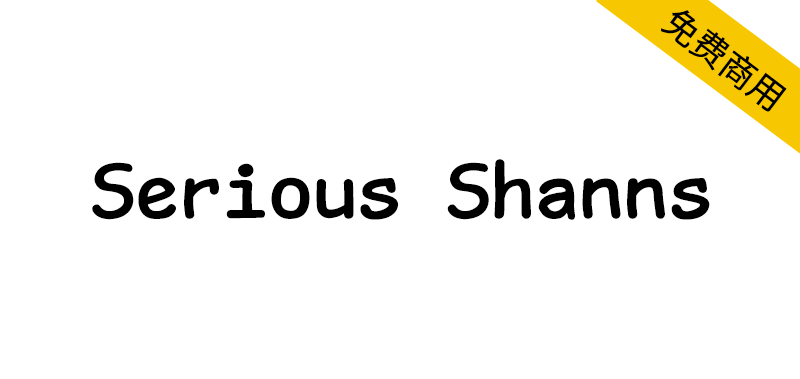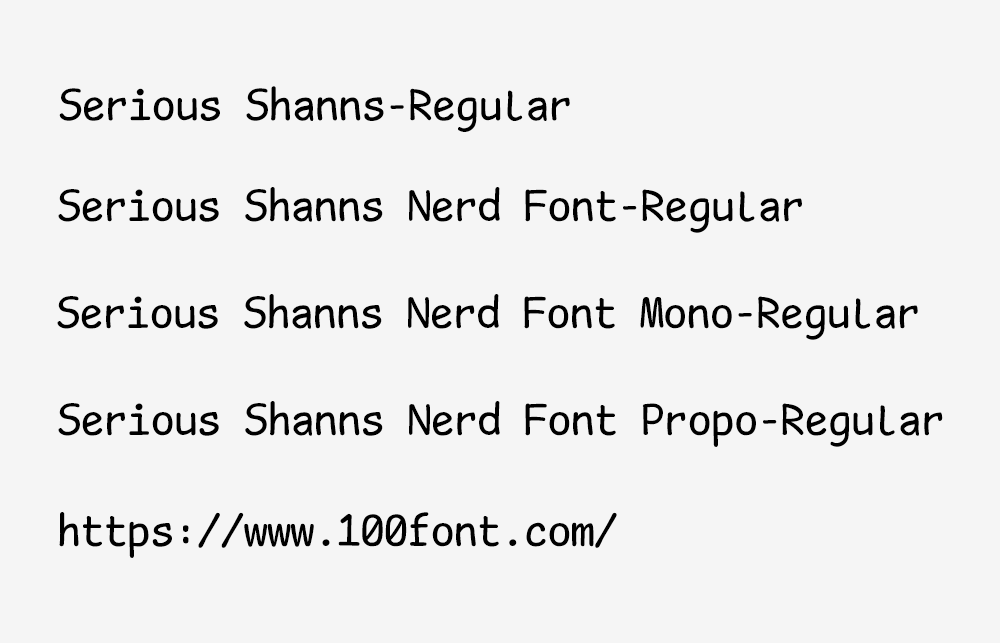
Serious Shanns是一款为趣味专业人士设计的清晰等宽字体——黑客界的Comic Sans,该字体基于dtinth的Comic Mono开发,而Comic Mono又衍生自Shannon Miwa的Comic Shanns,另可参考Jesús González的Comic Shanns Mono字体
Serious Shanns 是一款清晰易读的等宽字体,其设计灵感源自我们既熟悉又喜爱的经典 Comic Sans 字体。它在保留原版趣味风格的同时,特别优化以适应专业编程环境的使用需求。
A legible monospace font for playful professionals. Comic Sans for hackers.This font is a fork of dtinth's Comic Mono, which in turn is a fork of Shannon Miwa's Comic Shanns (version 1). See also Jesús González's Comic Shanns Mono
Serious Shanns is a legible monospaced font made to resemble the classic Comic Sans font we all know and love. It is designed to be suitable for use in a professional coding environment while retaining the playfulness of the original